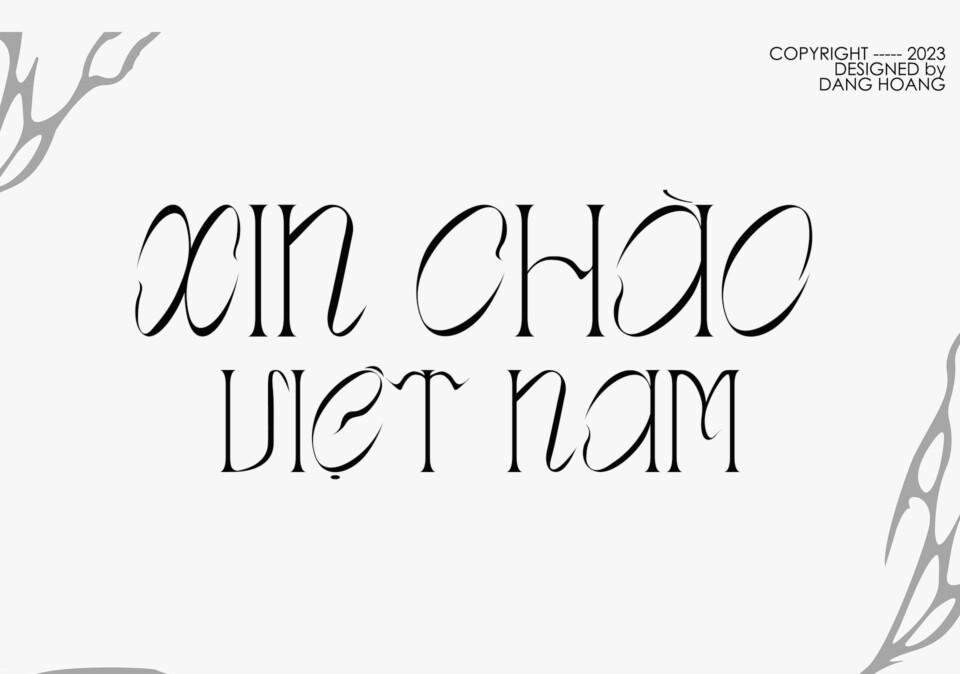
Font Tiếng Việt Deconstructed
Giới thiệu về bộ Font Tiếng Việt Deconstructed
Trong thế giới đồ họa hiện đại, việc lựa chọn Font Miễn Phí chất lượng đóng vai trò then chốt trong việc tạo nên hồn cốt cho tác phẩm. Font Tiếng Việt Deconstructed nổi lên như một hiện tượng nhờ phong cách thiết kế độc bản và phá cách. Đây là bộ font mang đậm hơi thở đương đại, nơi các nét chữ được tách lớp và cấu trúc lại một cách đầy tính nghệ thuật. Việc sử dụng Font Tiếng Việt Deconstructed không chỉ giúp nội dung trình bày trở nên ấn tượng mà còn giúp học sinh, sinh viên tiếp cận với tư duy thiết kế mới mẻ.
Ưu điểm vượt trội của Font Tiếng Việt Deconstructed
Thiết kế độc đáo và linh hoạt
Đúng như tên gọi, bộ chữ này mang phong cách “giải cấu trúc”, tạo cảm giác chuyển động và chiều sâu không gian. Từng đường nét trong Font Tiếng Việt Deconstructed được chăm chút tỉ mỉ, đảm bảo tính thẩm mỹ cao ngay cả khi đứng độc lập hoặc kết hợp trong các biểu ngữ học đường. Đây là lựa chọn lý tưởng cho các bạn trẻ muốn thể hiện cá tính riêng thông qua các bài thuyết trình hay dự án sáng tạo cá nhân.
Khả năng hiển thị và ứng dụng
Dù có cấu trúc phức tạp, font chữ này vẫn đảm bảo khả năng đọc tốt trên cả định dạng in ấn lẫn kỹ thuật số. Bạn có thể sử dụng nó để làm tiêu đề bài báo tường, thiết kế áo lớp hoặc trang trí bìa sách. Sự tương thích cao giúp người dùng dễ dàng cài đặt trên nhiều phần mềm thiết kế phổ biến hiện nay.
Kết luận và trải nghiệm người dùng